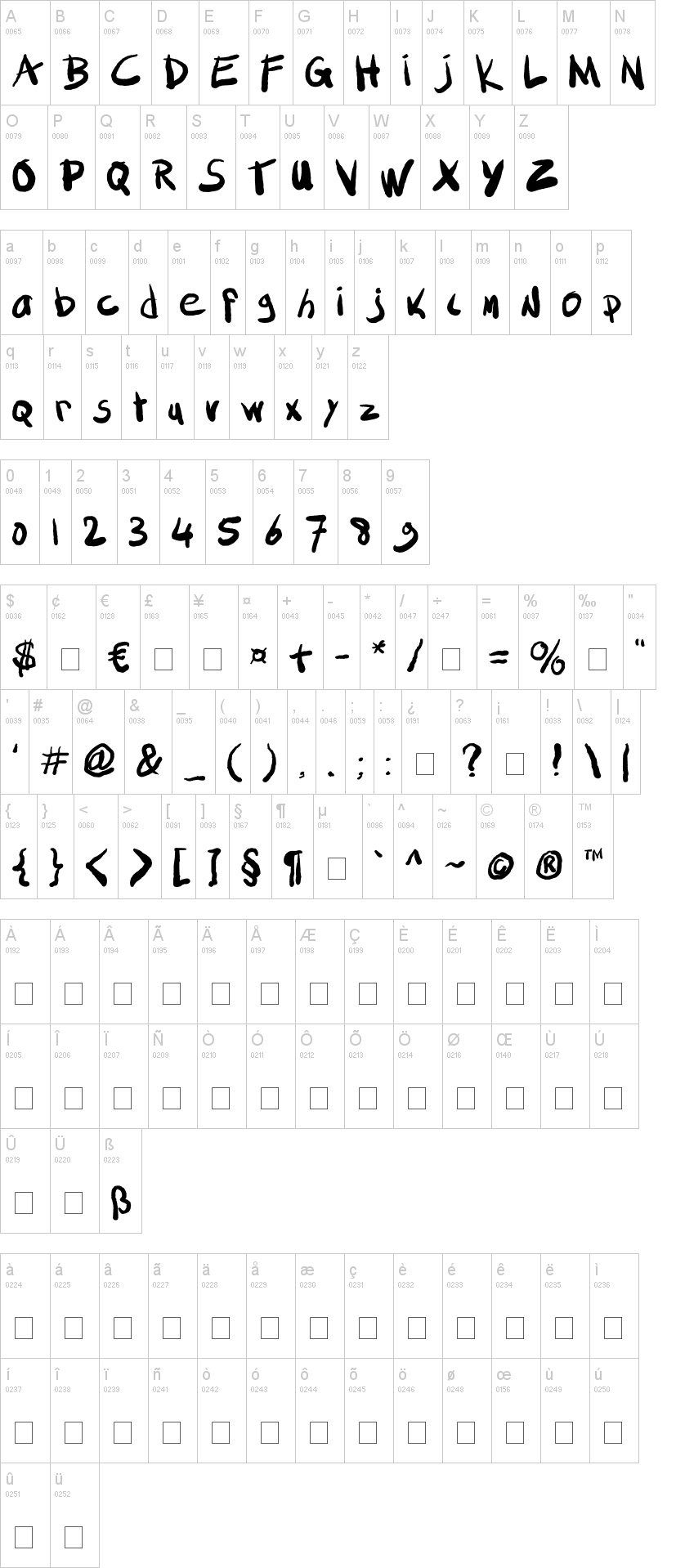
SML Fat Marker
SML Fat Marker 是一款粗体手写体字体,由英国设计师SML设计。它的特点是拥有古典的外观,却又具有现代感。它的字形有着粗壮的线条和粗犷的角度,具有鲜明的个性。它的字体特点适用于品牌标识,标题,海报,T恤,网页和其他设计中。
SML Fat Marker是一款非常不错的手写艺术字体,具有很好的视觉感,适合于文化类的宣传设计、商业类品牌的广告和产品包装设计以及个性化文字排版等较多场景。
SML Fat Marker字符映射图